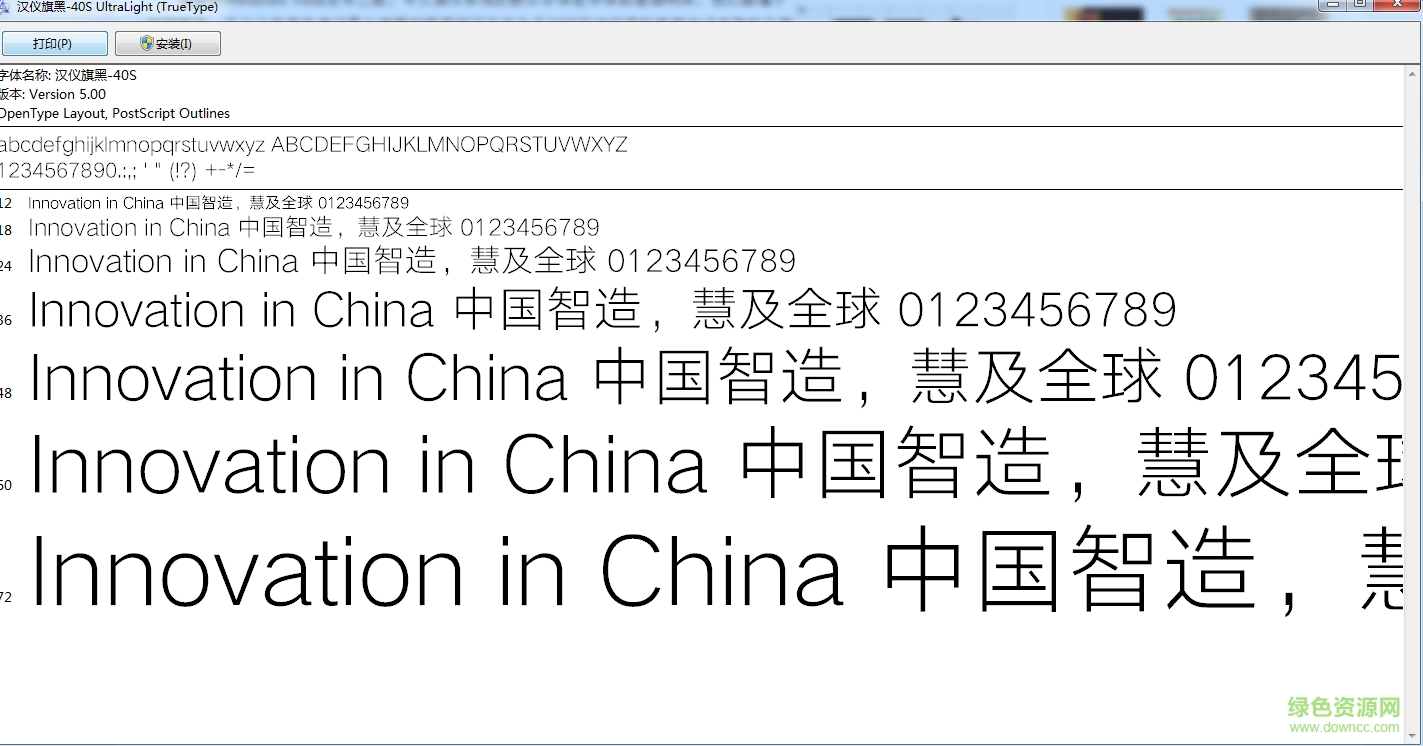
hyqihei dzs 字體又叫漢儀旗黑40s字體,字體設(shè)計合理,一筆一畫都十分的工整對稱,實(shí)用性強(qiáng),易于閱讀,一般用于標(biāo)題,導(dǎo)語等方面,需要的小伙伴趕緊下載吧!
hyqihei dzs適用于標(biāo)題或需要引起注意的醒目按語或批注,因為字體過于樸素,所以不適用于排印正文部分。
橫平豎直字見方 ,大小粗細(xì)一個樣 ,上緊下松要記牢 ,筆畫穿插又避讓 ,自隙均勻要講究 ,整齊美觀又大方